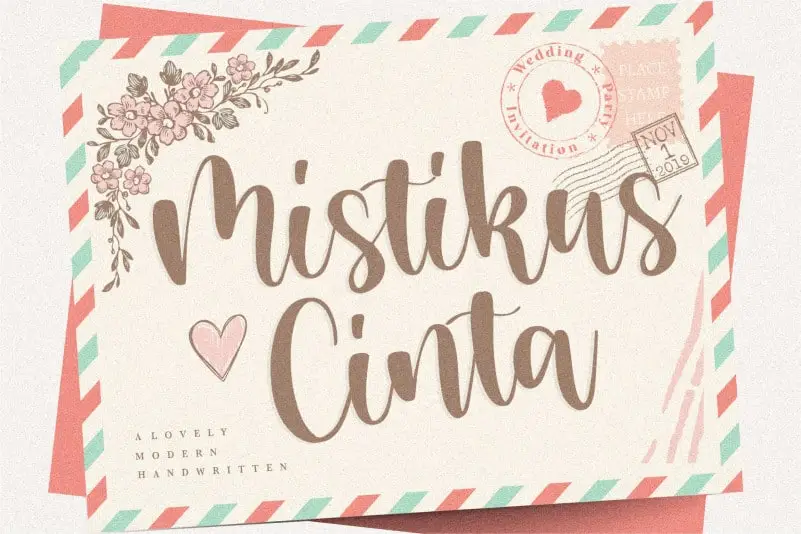
Mistikus Cinta Handwritten Font – Download Grátis
A fonte Mistikus Cinta Handwritten é perfeita para qualquer projeto que busca uma textura autêntica e charmosa. Seja ela aplicada nas embalagens de produtos, a criação de um projeto de marca inovador, o design de uma revista, as postagens em mídias sociais, ou mesmo no registro daquela grande celebração: casamentos. Esta fonte delicadamente escreveu palavras em um estilo autêntico e natural, tornando-a não apenas útil para expressar os textos acima do fundo, mas também uma adição encantadora ao seu design final. Com suas linhas fluidas e aveludadas, Mistikus Cinta Handwritten é mais do que uma opção de fonte; ela é uma sugestão de estilo, capaz de dar vida aos teus projetos digitais, dando-lhes um toque único e memorável.